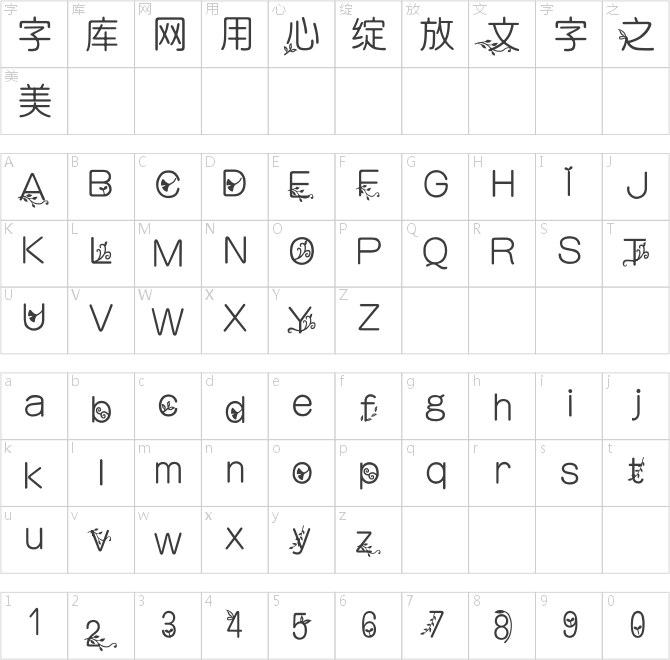
夜夜相思體
羿創(chuàng)字庫
夜夜相思體字體羿創(chuàng)夜夜相思字庫是一款讓人賞心悅目、百看不厭的中文字體,適合各類廣告和產(chǎn)品包裝設(shè)計應(yīng)用,字體大小2.59MB,格式為ttf字體,上傳用戶是浪遍塞納河的,作者/版權(quán)方為羿創(chuàng)字庫